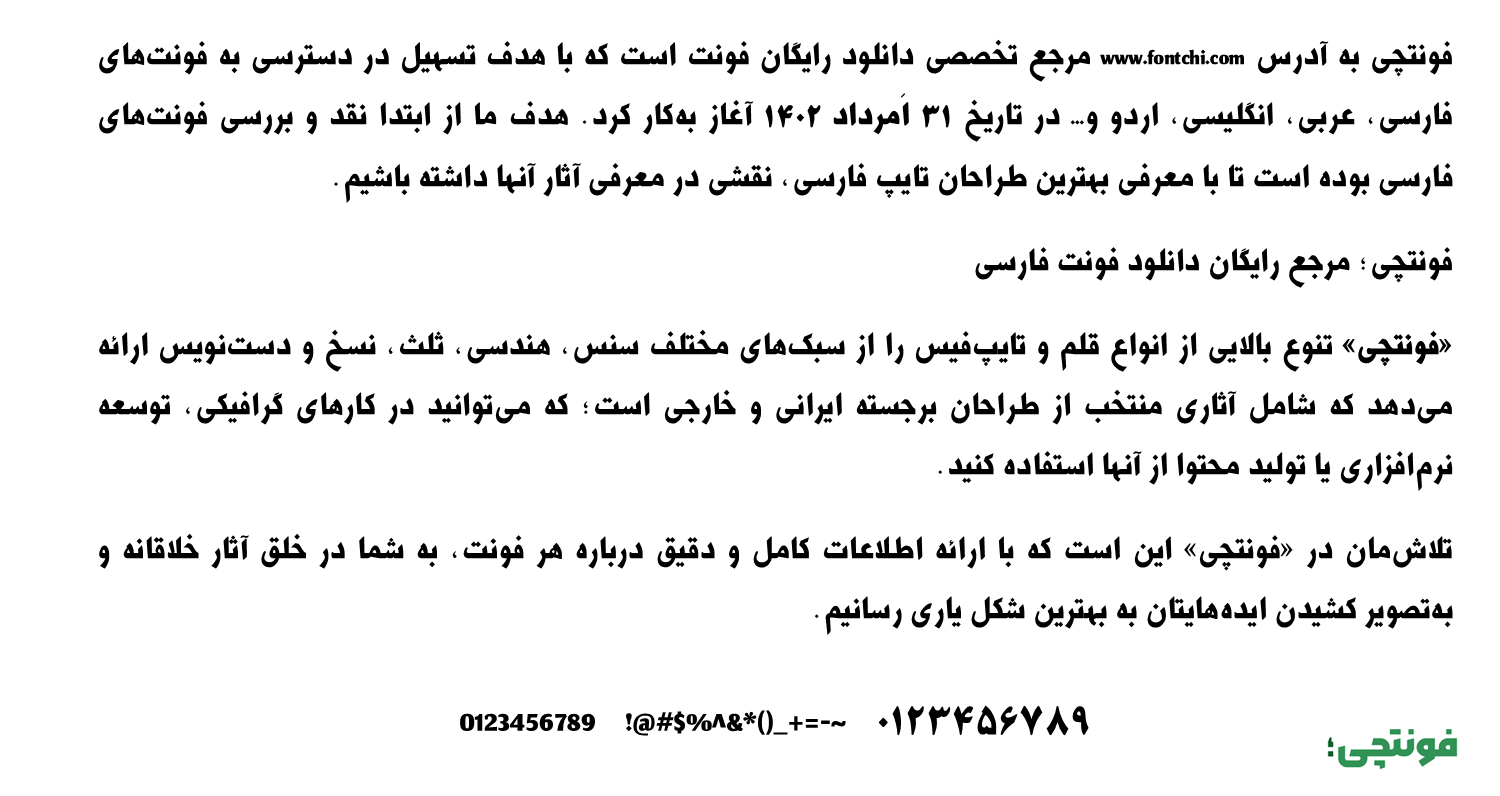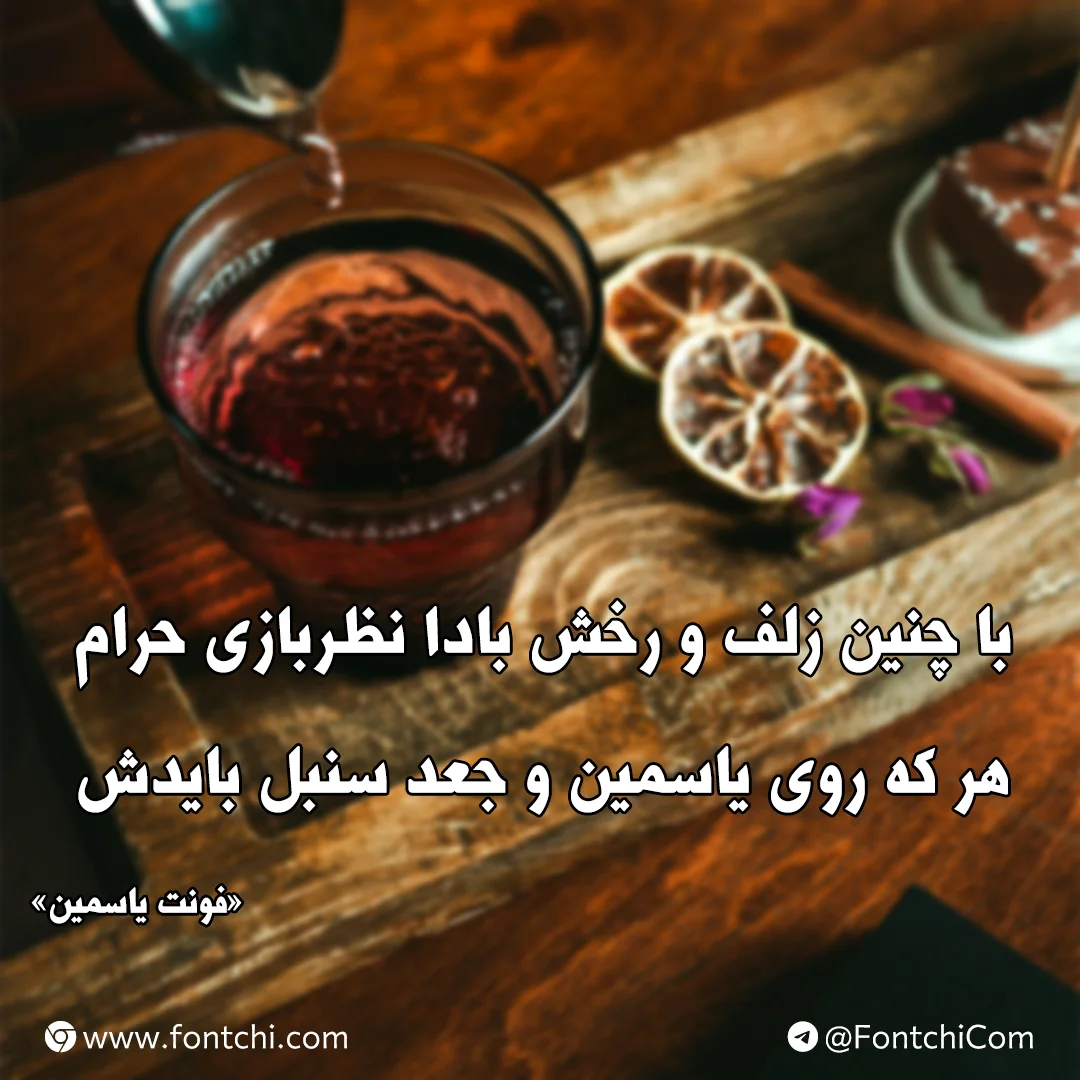
فونت یاسمین (A Yasamin)
| نام | آ یاسمین |
| نام نمایشی | A Yasamin |
| طراح | امید کردی |
فونت یاسمین یا آ یاسمین (به انگلیسی: A Yasamin) از سری فونتهای فارسی رایگان فارسی است که در سبک نسخ طراحی شده است. این فونت برای استفاده در متون بلند مناسب است که در عین ارائه وزن معمولی Regular، اما ظاهری سیاه و نسبتا بولد دارد.
این فونت توسط امید کردی طراحی شده و در دسته سری فونتهای A قرار دارد. در طراحی حروف این فونت فارسی، شاهد ضخامت یکسان نیستیم و همچنین گردی و چشمی حروف ساختاری متفاوت از یکدیگر دارند.
فونت یاسمین از زبان فارسی پشتیبانی کاملی دارد و با توجه به تشابه رسمخط عربی، میتوانید برای این زبان و سایر زبانهای مشابه نیز استفاده کنید. هرچند که ممکن است برخی گلیفها و کاراکترها با محدودیت مواجه باشید.
برای مثال در بخش اعداد این فونت شاهد استفاده از اعداد تماما فارسی هستیم و خبری از اعداد عربی «٤٥٦» استاندارد نیست. برای زبان عربی نیز اعداد «۴۵۶» تایپ خواهد شد که جزو کاستیهای این فونت است.
از سوی دیگر در بخش حروف لاتین با اینکه ساختار طراحی حروف مشابه با حروف فارسی است، اما در مقابل ضخامت کمتری نسبت به حروف فارسی دارد که در این صورت شاید مجبور به استفاده از فونت جایگزین دیگری برای زبان انگلیسی باشید.
از جمله کاربردهای این فونت زیبا میتوان در حوزه چاپ اشاره کرد که برای متون طولانی مانند متن کتاب و مجله، اعلامیهها و به طور کلی متون بلند مناسب خواهد بود. همچنین از این فونت میتوانید برای ساخت عکسنوشته در شبکههای اجتماعی یا تصاویری که ساختار متنی برای انتقال محتوای متنی مانند پوسترها دارند استفاده کنید.
خوانایی این فونت برای متون بلند عالی است و به گونهای نیست که در دراز مدت باعث خستگی چشم شود.